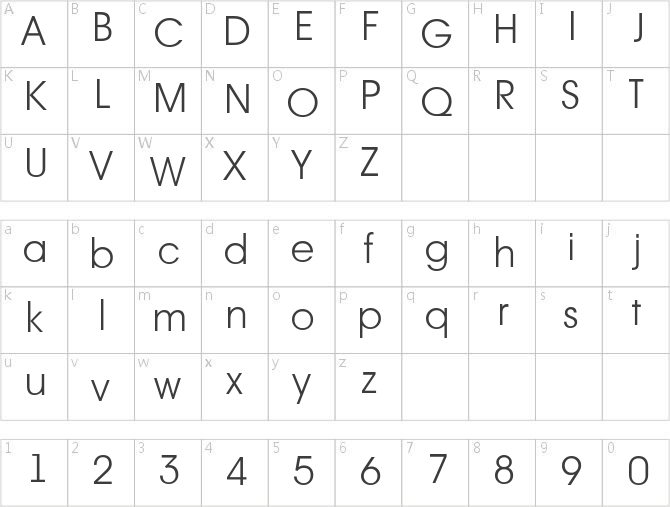
字体名称: a_Avant
a_AvanteLt-Light
a_AvanteLt-Light介绍
a_AvanteLt-Light字体字库是一款让人赏心悦目、百看不厌的英文字体,适合各类广告和产品包装设计应用,字体大小0.04MB,格式为ttf字体,上传用户是雅迪,作者/版权方为未知
a_AvanteLt-Light效果图